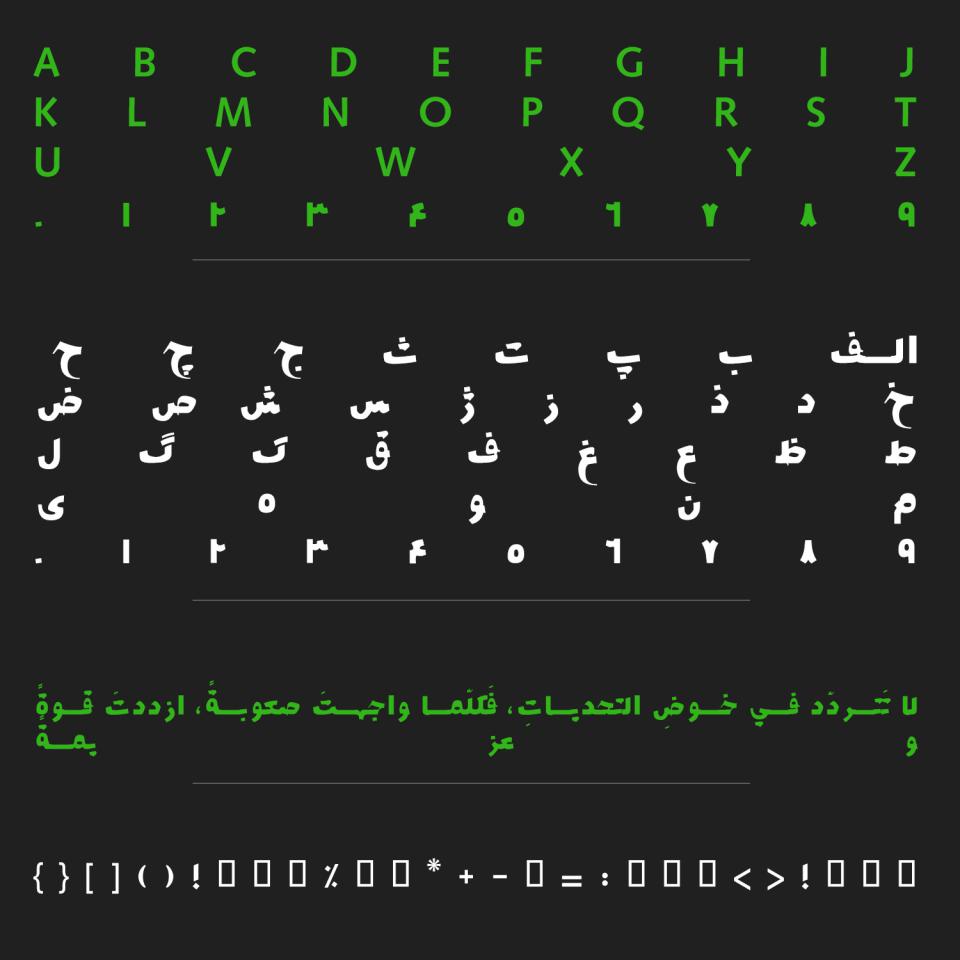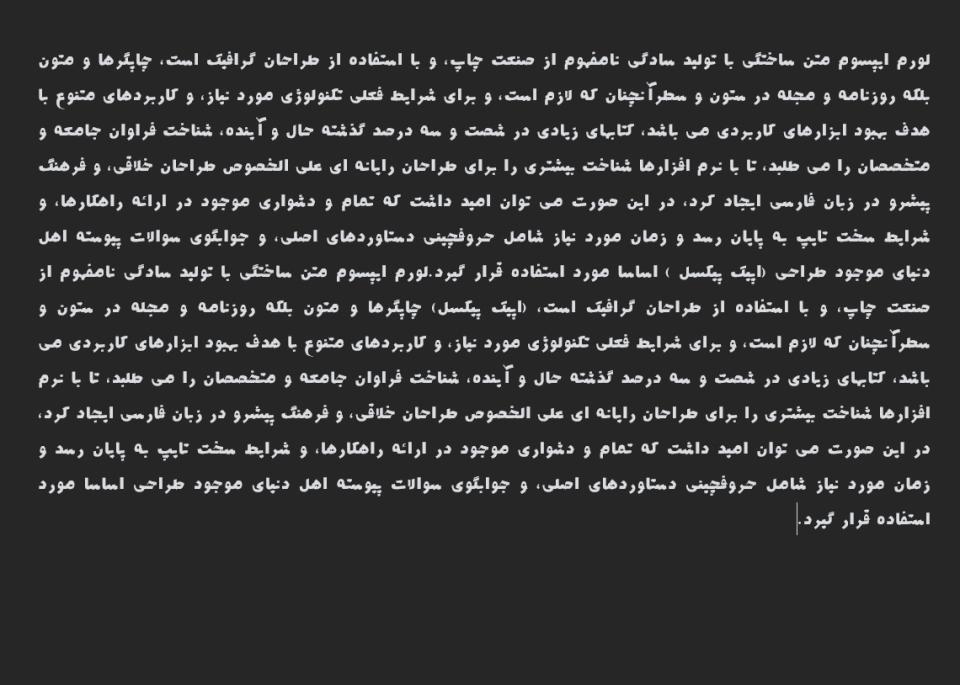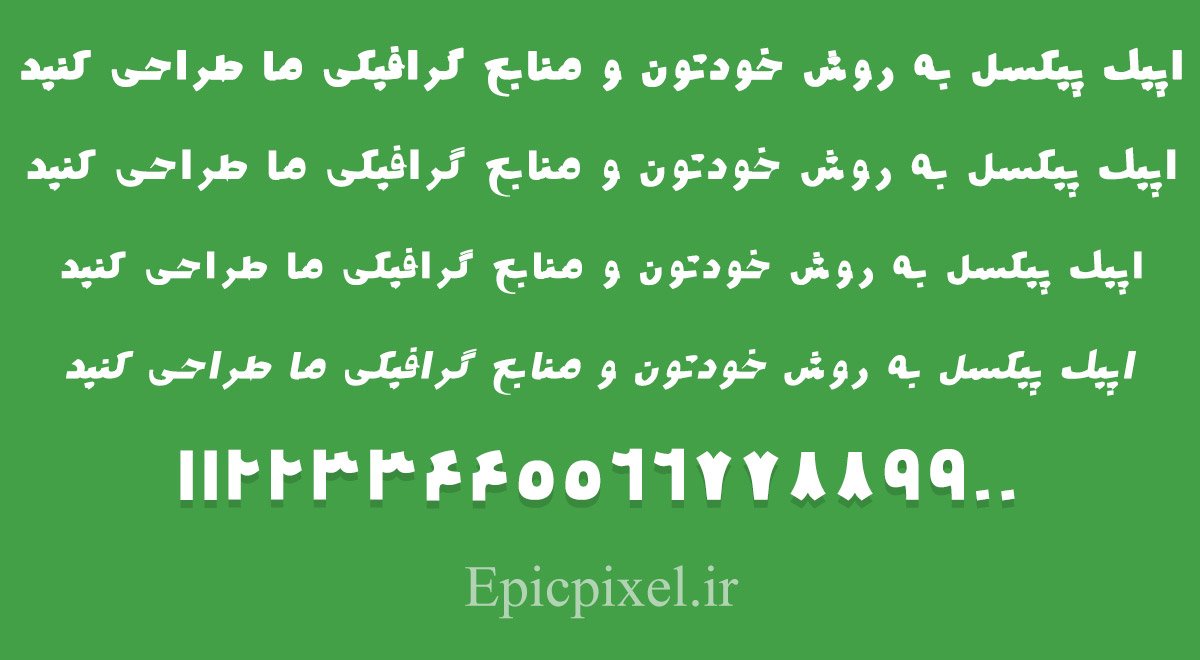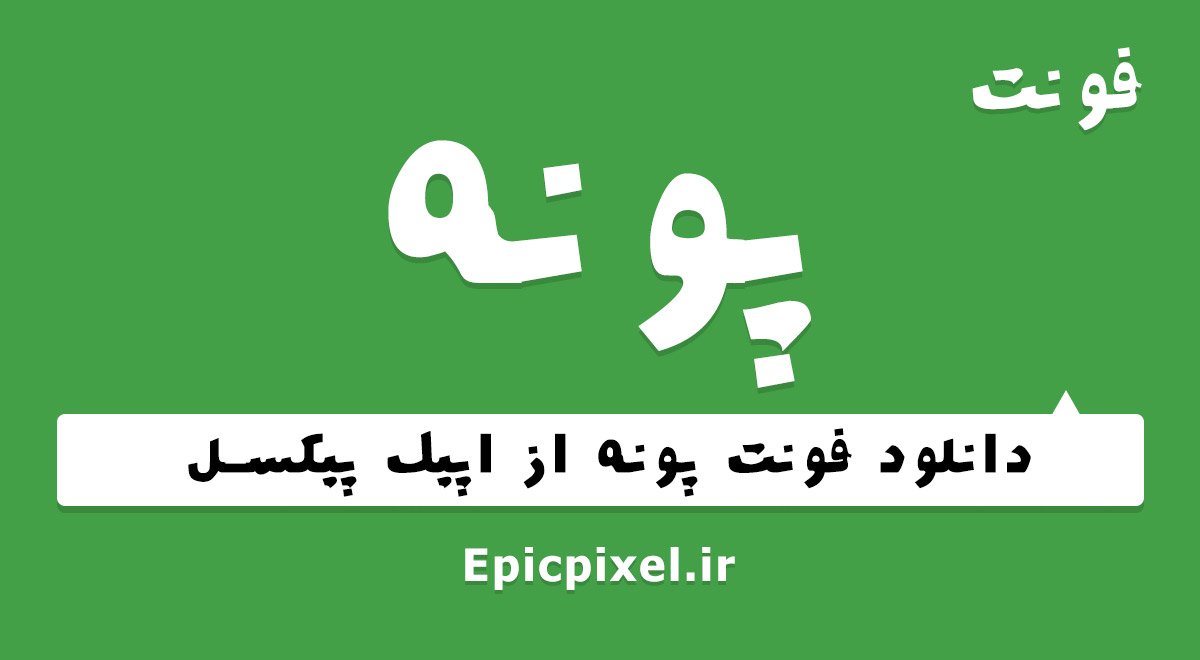
2 فونت پونه فارسی
فونت پونه فارسی، انتخابی ایدهآل برای کسانی است که به دنبال ظرافت و خوانایی در نوشتههای خود هستند. این فونت با طراحی منحصر به فرد خود، ترکیبی دلنشین از خطوط نرم و ساختار قوی را ارائه میدهد و به همین دلیل، هم در متنهای طولانی و هم در عناوین کوتاه، چشمنواز و کاربردی است.
یکی از ویژگیهای برجسته فونت پونه، هماهنگی بینظیر حروف با یکدیگر است که باعث میشود متن روان و یکدست به نظر برسد. این ویژگی به ویژه در طراحی لوگو، پوستر و بستهبندی که زیبایی بصری اهمیت زیادی دارد، بسیار ارزشمند است. همچنین، فونت پونه از زبان فارسی به طور کامل پشتیبانی میکند و تمامی حروف و نشانههای این زبان را به درستی نمایش میدهد.
اگر به دنبال فونتی هستید که هم زیبایی داشته باشد و هم خوانایی بالایی را ارائه دهد، فونت پونه فارسی گزینهای عالی برای شماست. این فونت به صورت رایگان در دسترس است و میتوانید به راحتی آن را دانلود و در پروژههای خود استفاده کنید. با استفاده از فونت پونه، نوشتههای خود را به سطح جدیدی از زیبایی و حرفهای بودن برسانید.